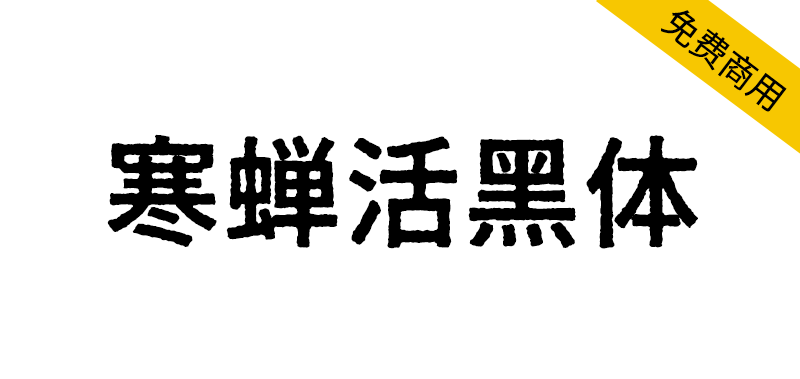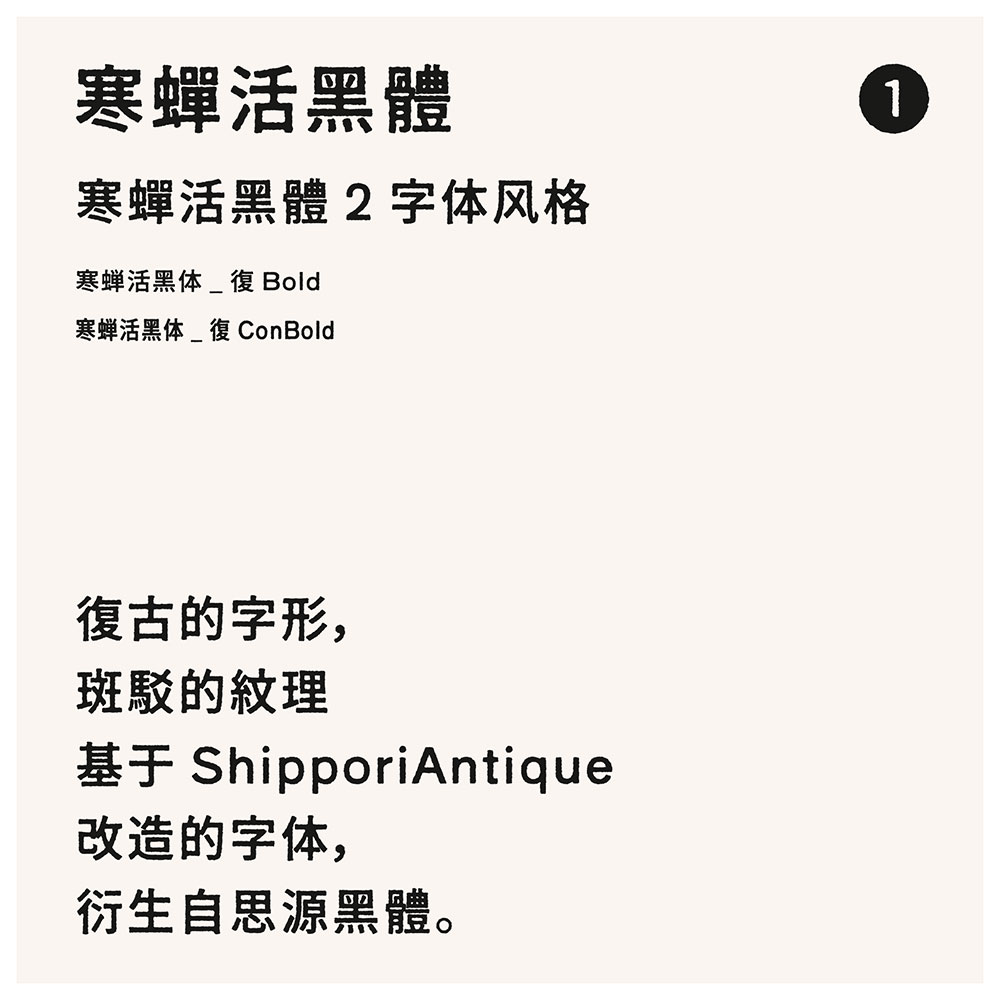
寒蝉活黑体是一个活字印刷字体项目,模拟印刷时的轻度油墨溢出,复古的字形,斑驳的纹理,基于Shippori Antique改造的字体,衍生自思源黑体。
本项目旨在已有的开源字体上修改模拟具有轻度油墨溢出的效果。此为新的尝试,使用较为复古的字形字体,不太适用于较正式的场合。本系列属于反向造字,将清晰的字体变得模糊,将顺滑流畅的曲线修改为驳杂的曲线。
值得注意的是和真实的印刷再扫描字体有较大差距。折中取轻度的斑驳效果,与原字体对比却又多了几分真实。或许对少量海报设计项目和新媒体有些许用处。